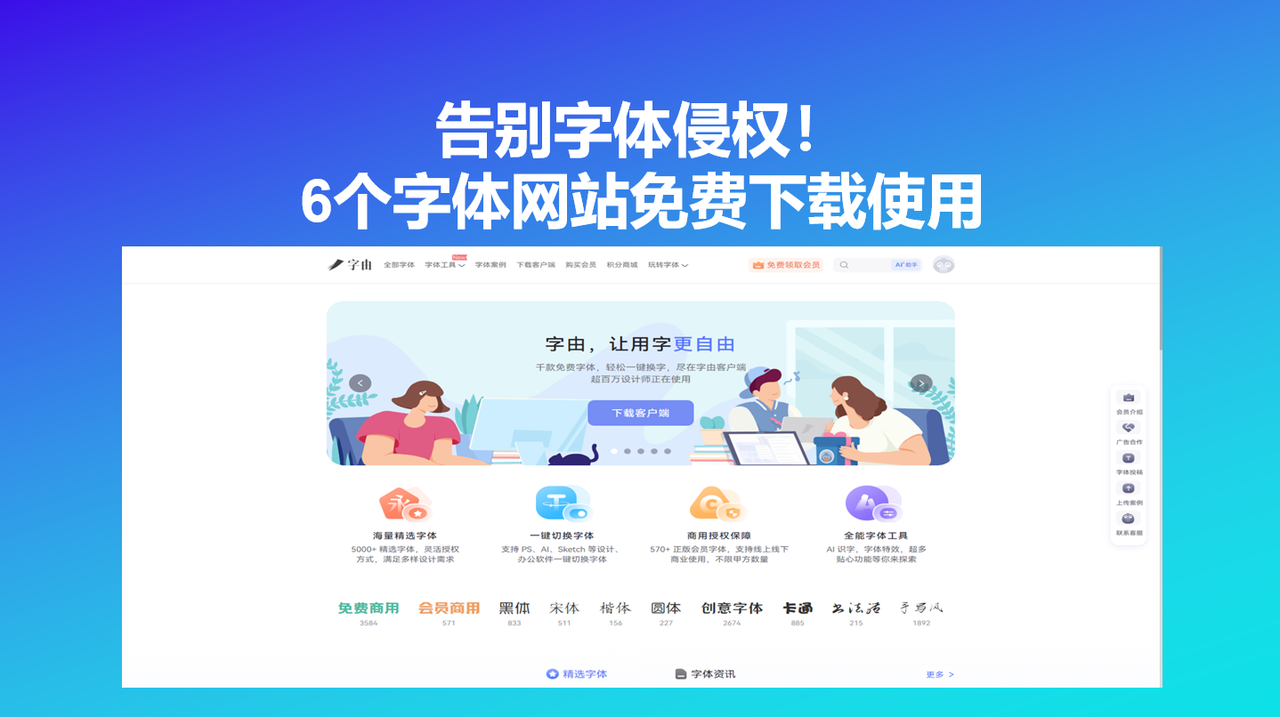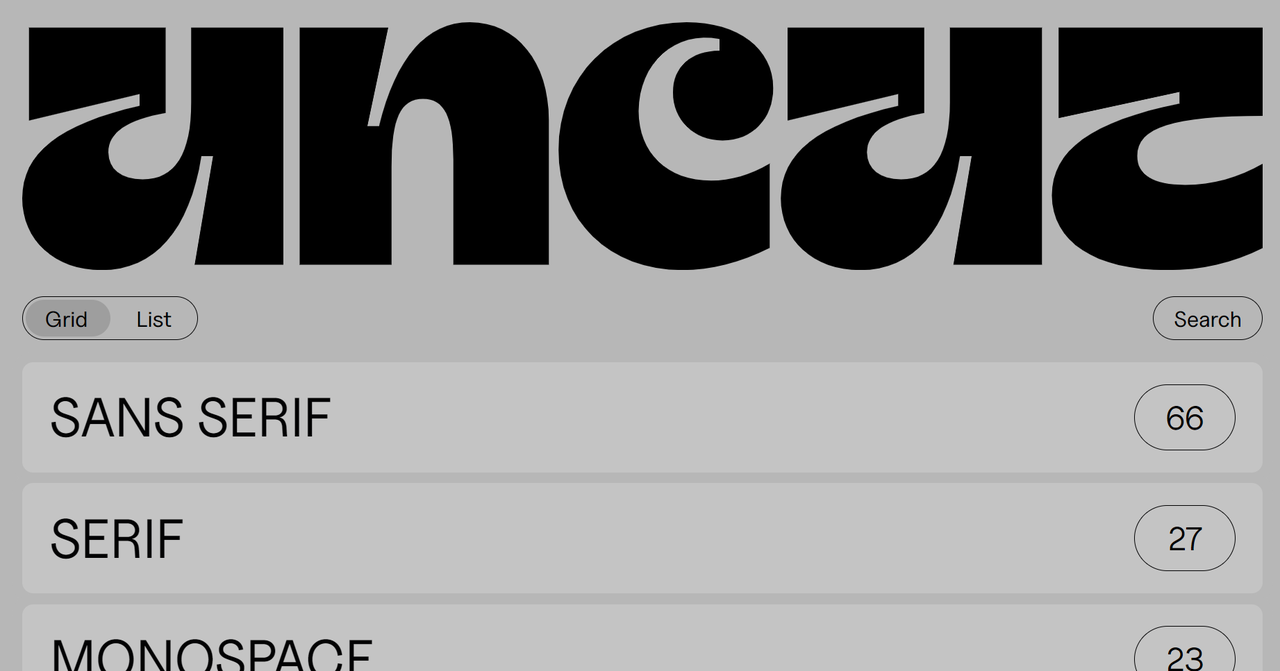
告别字体侵权!6个字体网站免费下载使用
如果是经常与设计打交道的人肯定知道,做设计的时候最怕的事情就是侵权,不论是图片还是所用的字体,每一项内容都有其特定的版权,有的是免费开源,有的则是仅限个人练习使用,有的则是需要付费以后才能够商用。但是我要提醒大家的是,这种和侵权相关的很多问题是可以轻松避免的,关键就在于要找对字体网站免费下载资源。现在有不少平台专门收集免费可商用字体,并且上面还会清楚地标注可用的途径,这样就可以帮你省去查找版权的时间和精力。那么今天我整理了 6 个可供字体免费下载使用的网站,需要的直接收藏!
字由是一个集字体库、字体管理和设计辅助于一体的平台。和一般的普通字体下载网站不同,字由的定位是“让用字更自由”——它不止让你能下载字体,更让你用起来方便、管起来省心。字体库方面,字由客户端内置了 5000 多款精选字体,其中超过 3500 款是免费可商用的,涵盖优设好身体、字由文艺黑、阿里妈妈东方大楷等热门字体。这些字体都来自厂商公开授权,下载前已经帮你筛选好授权类型,不用担心误用侵权。在使用体验式,字由支持多软件一键切换字体,不用额外下载字体包也不需要安装重启,这样就大大地提高了工作效率。而且字由提供个人云字库,可以上传本地字体到云端,换设备登录自动同步。如果你在公司、家里多台电脑办公,这个功能很实用。另外,字由也支持多种 AI 在线工具,包括 AI 识字、 AI 智能擦除并恢复背景等,这可以让设计创作更加专注于设计本身。
2、Uncut
Uncut 是一个专门收集当代高质量免费字体的平台,由设计师合作维护。它的特点是“精”而不是“多”——每一款字体都经过筛选,确保设计水准在线。网站上的每一款字体都标注了设计师的相关信息和是授权方式,里面的字体几乎都是免费可商用的,安装即用。说到 Uncut,就不得不提它的当家字体——Uncut Sans。这是一款由 Kasper Nordkvist 设计的无衬线字体,被很多人评价为 Helvetica 的免费平替。如果你在做品牌设计,需要一些有设计感的西式字体,这个网站会很适合你。
3、Grilli Type
Grilli Type 是一家总部位于瑞士的字体设计公司,以精致的设计和严谨的工艺著称。他们的字体作品在全球范围内被广泛应用,在专业字体圈口碑很好。Grilli Type 的字体风格涵盖经典、现代、展示等类别,虽然大部分的字体需要付费购买但是免费的部分也足够一般设计师下载使用了,即便不选择付费购买,仅仅是在这个网页里转一圈也能够汲取设计灵感,提升对字体的审美能力。如果你是专业设计师,正在找一些高品质的衬线体或无衬线体做品牌项目,可以收藏这个网站。
4、Velvetyne
Velvetyne 是一个很特别的字体平台——它把自己定位为“自由字体合作社”,由一群设计师、程序员和字体爱好者共同维护。网站上所有的字体都开源免费,可以自由使用、修改、再分发。相当于一个小型字体社区,这也说明了这个网站的字体风格为何如此多元化,有实验性的展示字体,也有复古感的标题字体,还有一些带着手工感的手写体。这里面的每一款字体也都附带相关信息和授权文件,下载就可以预览文字效果。
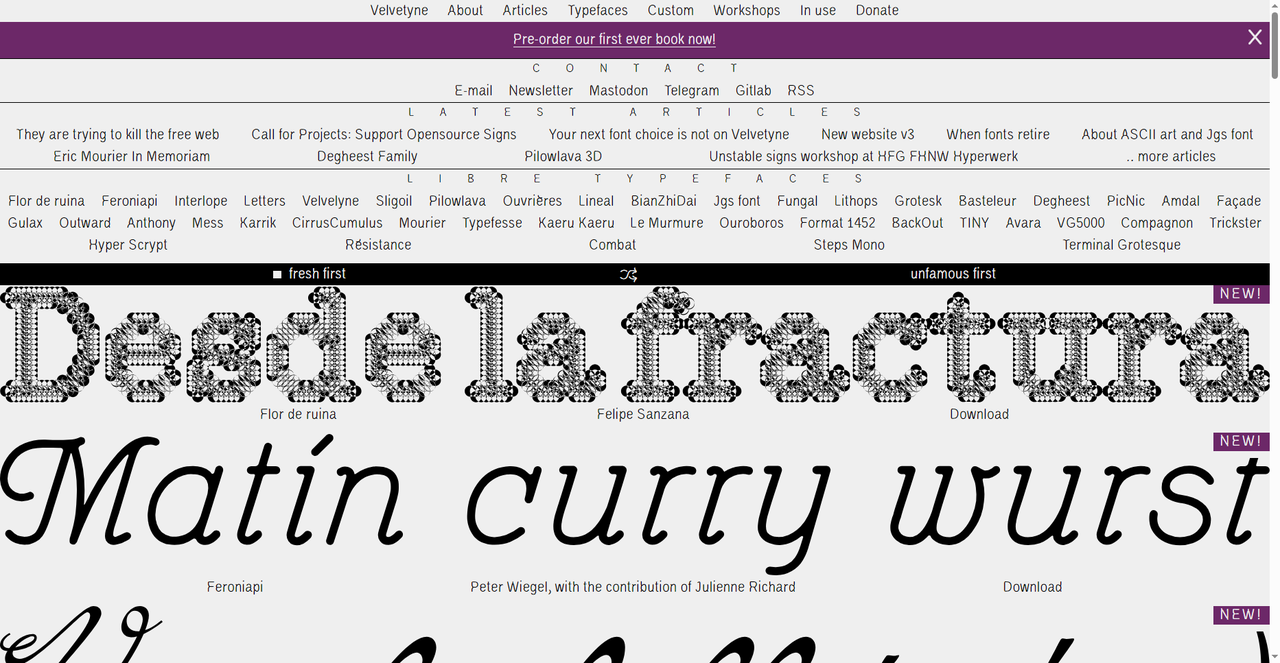
5、Adobe Fonts
Adobe Fonts 是 Adobe 公司旗下的字体平台,如果你是 Adobe 软件用户(Photoshop、Illustrator、InDesign 等),开通 Creative Cloud 订阅后就可以免费使用 Adobe Fonts 上的数千款字体。Adobe Fonts 的字体库非常庞大,涵盖各种类型的字体,涉及面非常广,如果你已经是 Adobe 软件用户并开通了 Creative Cloud 订阅,这个字体库对你来说会非常地顺手。这个网站十分推荐给本来就在用 Adobe 系列软件的设计师们。
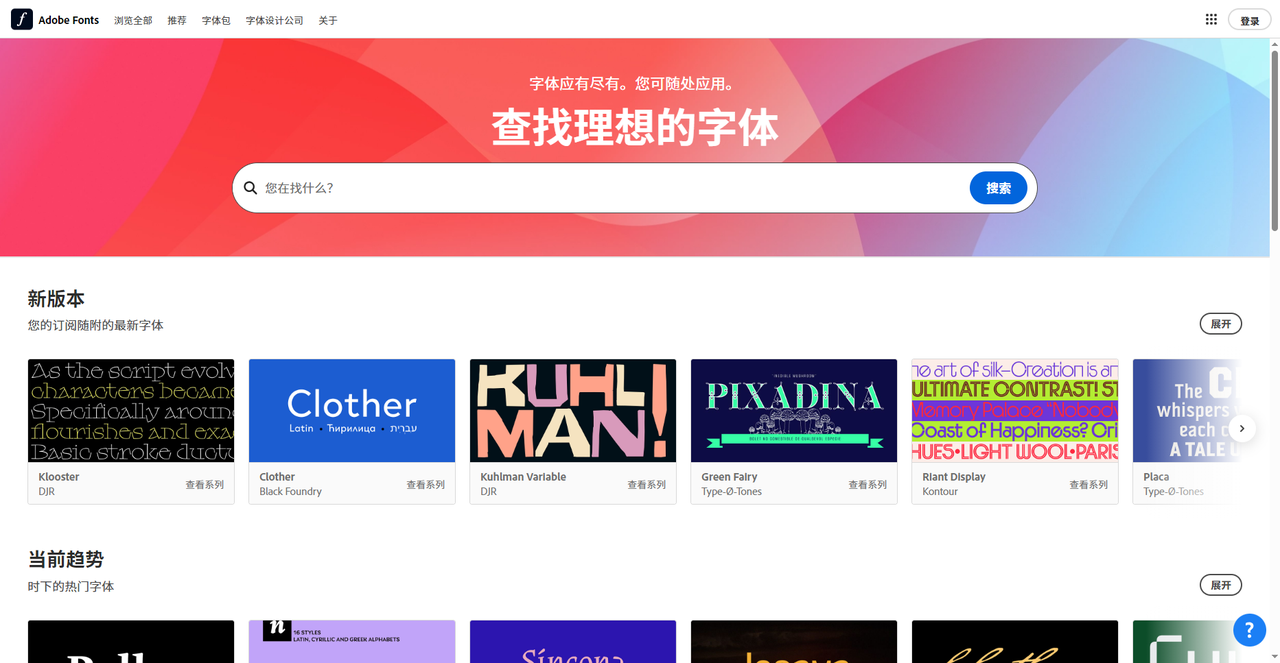
6、Behance
Behance 是 Adobe 旗下的设计师作品展示平台,每天都有大量设计师上传自己的作品。虽然 Behance 本身不是严格意义上的字体免费下载网站,但搜索 “free font” 能发现很多设计师分享的免费字体项目。这些字体都很有个性,风格比常规字体网站更前卫。如果你在寻找一些独特的、有设计感的字体,可以来这个网站,说不定会有意外收获,不过需要注意的是要确认一下字体的授权说明,确保可以商用。